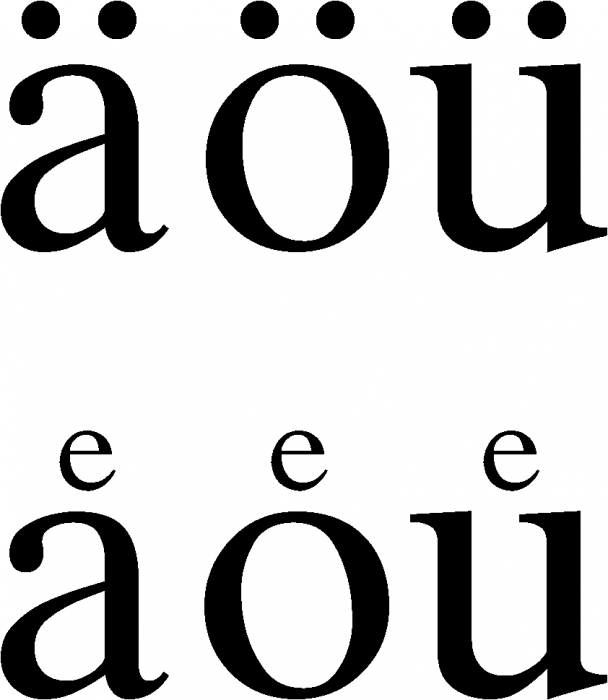
Schrift mit "alten" Umlaute gesucht. ä ö ü
Bin auf der Suche nach einer Serifen-Schrift mit einer Version von ä, ö und ü wie angehängt? Bild stammt von Wikipedia. Kann mir da jemand weiterhelfen?